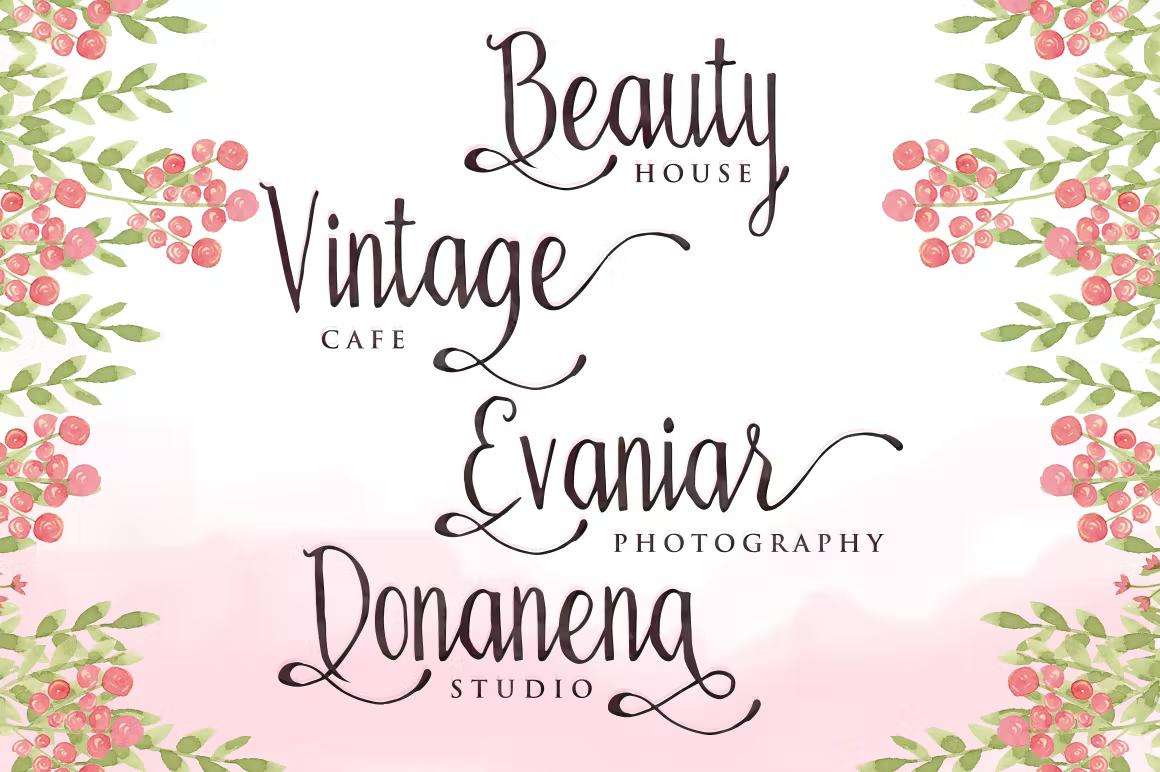
Bellanie Script Font
Description de Bellanie Script Font
Présentation de Bellanie Script
Bellanie Script est une police de caractères faite à la main. Bellanie Script convient aux invitations de mariage, à toutes les cartes de vœux, au style de design rétro/vintage ou à tout design nécessitant une touche naturelle et personnelle. Mélangez et associez les personnages alternatifs pour ajouter un message attrayant à votre design.